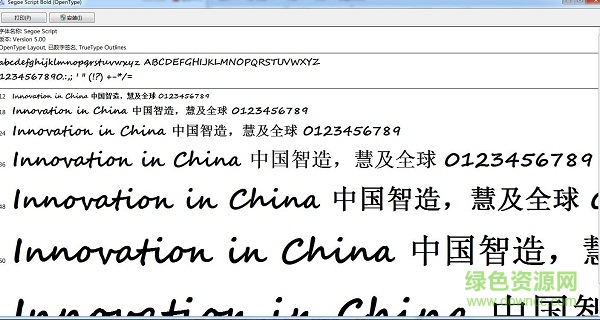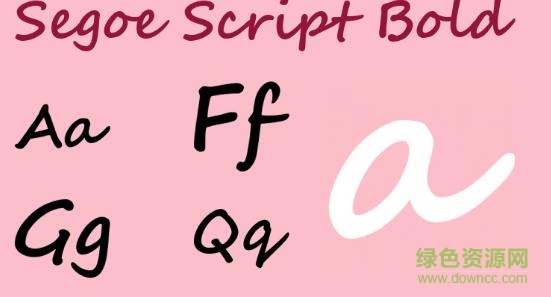
segoe script bold粗體字體是一款手寫(xiě)風(fēng)格的英文字體,時(shí)尚優(yōu)雅,自由灑脫,適合用在海報(bào)設(shè)計(jì)、包裝設(shè)計(jì)等領(lǐng)域,綠色資源網(wǎng)還有更多優(yōu)質(zhì)廣告字體免費(fèi)提供,有需要者快來(lái)下載吧!
英文文字大致分成三類(lèi),襯線體,無(wú)襯線體和其他字體。其他字體包括哥特體,手寫(xiě)體和裝飾體!